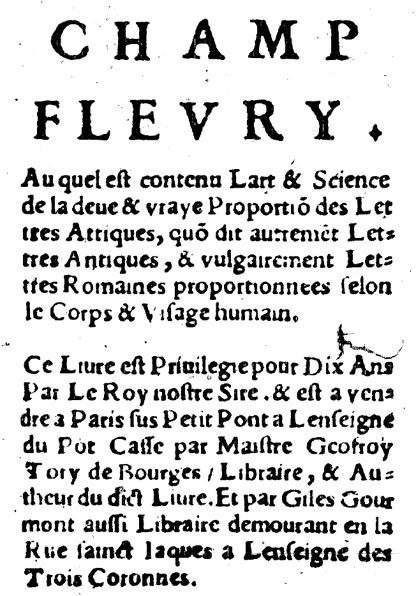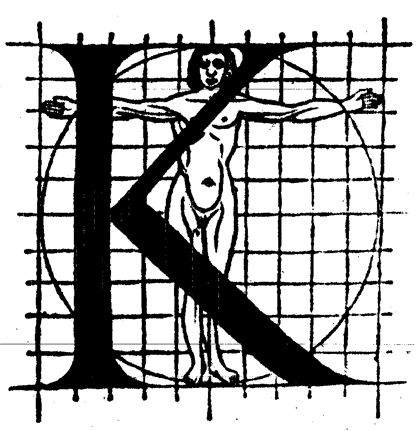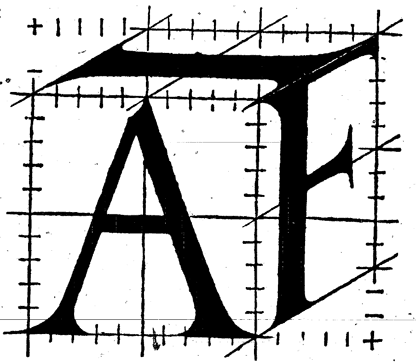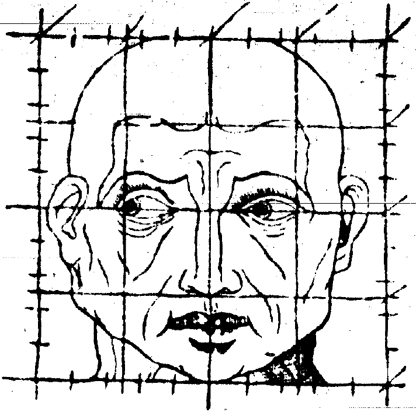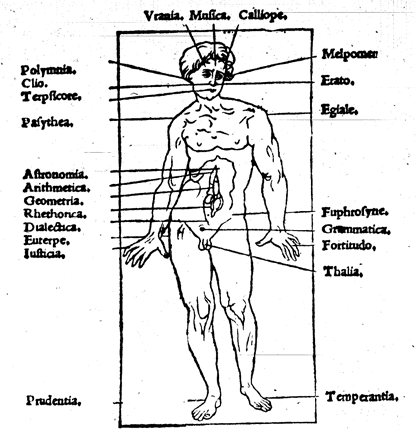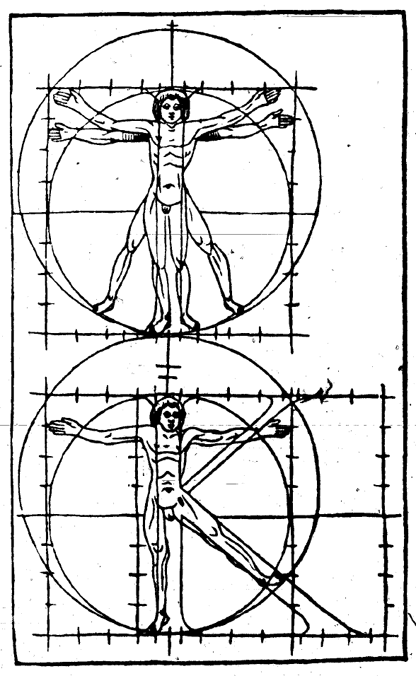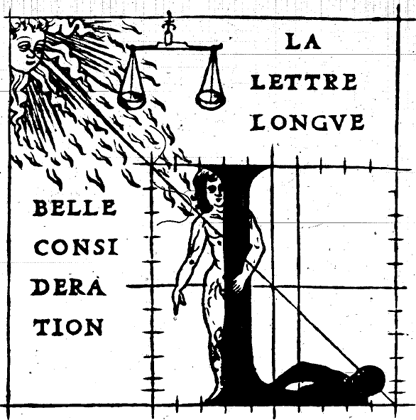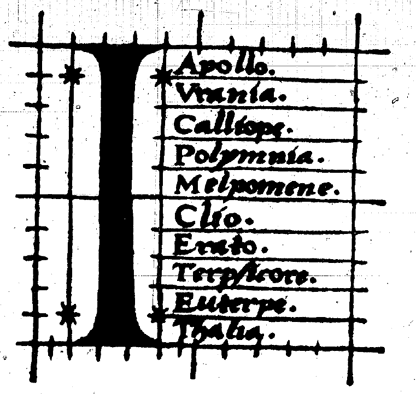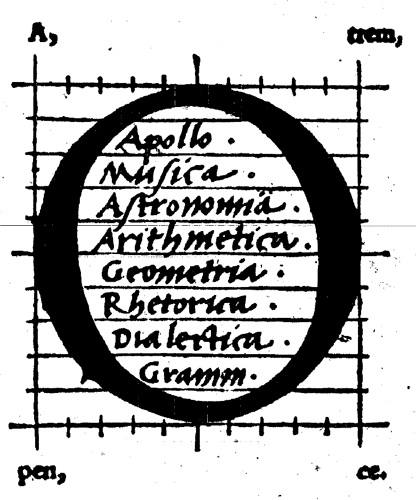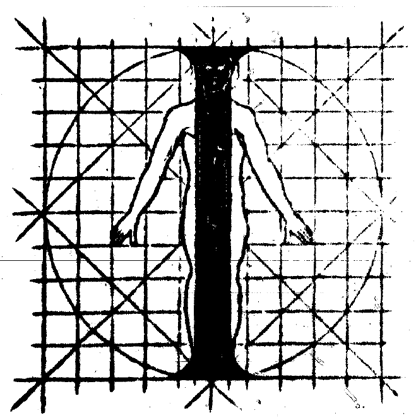
En consultant les champs de recherche de Gallica, la bibliothèque numérique de la BnF, on constate d’abord qu’il s’agit (à moins d’une erreur grossière de ma part) du seul ouvrage consacré à la typographie ayant bénéficié d’une numérisation par Gallica. Et quelle numérisation. Dans n’importe quel atelier de reproduction du secteur privé, on aurait jeté ces documents. Poussières, cheveux, exposition mal réglée… autant dire qu’il s’agit là d’un document amateur inutilisable par les professionnels du métier. En explorant plus loin, nous avons pu nous rendre compte que les autres ouvrages ne bénéficient pas d’un traitement plus favorable. Le process de reproduction est détestable alors qu’il s’agit du Seul document traitant de la typographie dans les ressources de la BnF. Il faut rendre grâce à des initiatives privées comme celui de Jacques André qui numérise en France le manuel typographique de Pierre-Simon Fournier que vous pouvez feuilleter ici .
Le travail de recherche de Geofroy Tory s’inscrit dans le champ des explorations philosophiques et artistiques du XVIe siècle. Nous sommes en pleine renaissance et les artistes, au contact de la médecine et des naturalistes cherchent à établir des vérités interdépendantes voire anthropomorphiques, entre nature et production humaine. Ainsi les constructions alphabétiques de Tory relèvent plus d’une construction de l’esprit que de celui d’un pur calligraphe. Nous sommes loin de la rigueur et de la modestie d’un Claude Garamond qui ne chercha aucune théorie à son invention que celui d’une meilleure lisibilité. Tory veut absolument se convaincre de l’existence de proportions divines qui régissent les formes humaines et alphabétiques. C’est à ses risques et périls, on le verra dans les années à venir. Je vous laisse découvrir ces quelques planches et vous trouverez au bas de cette note le fichier PDF complet de l’ouvrage mis à dispo par la BnF sur leur serveur FTP. Je l’ai téléchargé, vous n’aurez plus qu’à faire un clic droit et l’enregistrer sur votre poste de travail.